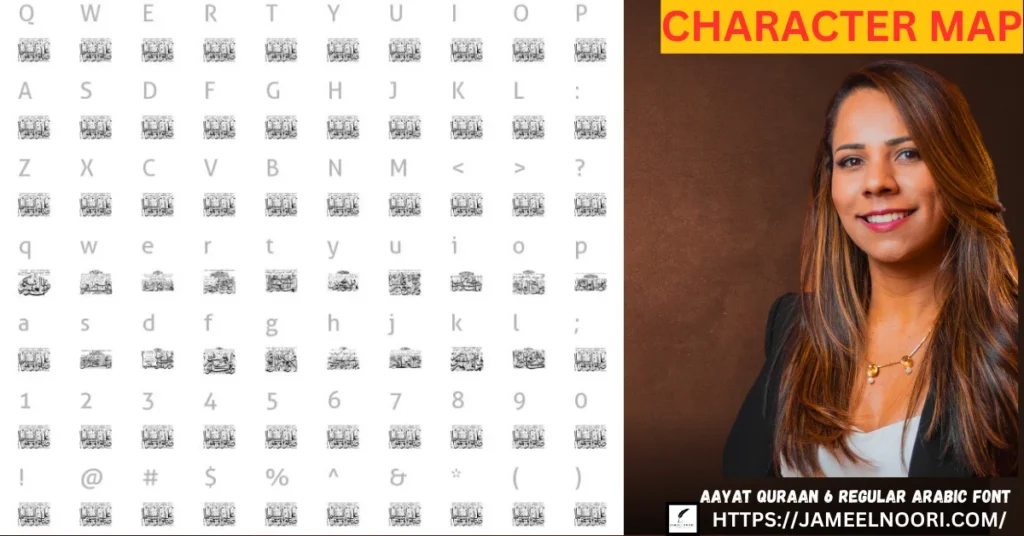
Aayat Quraan 6 Regular Arabic Font ek Islamic calligraphy based Arabic font hai jo Quranic text, Islamic quotes, aur Urdu Arabic designs ke liye perfect use hota hai. Ye font specially Pakistan, Lahore, Karachi aur Islamic designing projects me bohot popular hai. Font ki readability aur smooth style isse designers aur students dono ke liye perfect bana deti hai.
Aayat Quraan 6 Regular Arabic Font Features (Best Highlights)
Is font ke unique features designers aur typing work me clear professional look provide karte hain:
- Quranic typography ke liye world-class calligraphy
- Smooth aur clear Arabic character shapes
- Mosque banners, Islamic posters, Quranic ayat design ke liye ideal
Why Aayat Quraan 6 Regular Arabic Font is Expert Choice?
Is font ko choose karne ke major reasons Roman Urdu me:
- Readability bohot strong hai
- Arabic aur Urdu dono ke liye professional
- Mosque banners aur Eid flyers ke liye best
- Islamic schools aur Quranic teaching centers me heavily used
Where to Use Aayat Quraan 6 Regular Arabic Font in Pakistan?
Niche usage points Pakistan ke graphic designers ke liye:
- Arabic poster designing
- Quran typing
- Islamic banners & flyers
- YouTube Islamic thumbnails
- Website Urdu Arabic headings
Aayat Quraan 6 Regular vs Other Arabic Fonts (Comparison Table)
| Feature | Aayat Quraan 6 | Standard Arabic |
| Quranic Clarity | ★★★★★ | ★★★☆☆ |
| Calligraphy Style | Elegant | Basic |
| Design Quality | Premium | Average |
Aayat Quraan 6 Regular TTF Arabic Font Character Map Overview
Character map section me Arabic letters ki smooth finishing aur clear spacing milti hai jo Quranic ayat ko professional touch deti hai. Ye font especially Islamic publishing, flyers, and digital calligraphy ke liye best consider hota hai.
What is Aayat Quraan 6 Regular Arabic Font used for?
It is mainly used for Quranic text, Islamic quotes, and Arabic calligraphy designs.
Does it support Urdu typing?
Yes, it supports Arabic and Urdu both.
Is it good for graphic designing?
Yes, it is highly recommended for posters, flyers, and banners.
Is this font suitable for YouTube thumbnail designs?
Yes, it gives a beautiful Islamic look to thumbnails.
How is the calligraphy quality?
Very elegant and professional for Islamic work.
Is it better than other Arabic fonts?
Yes, especially in Quranic readability.